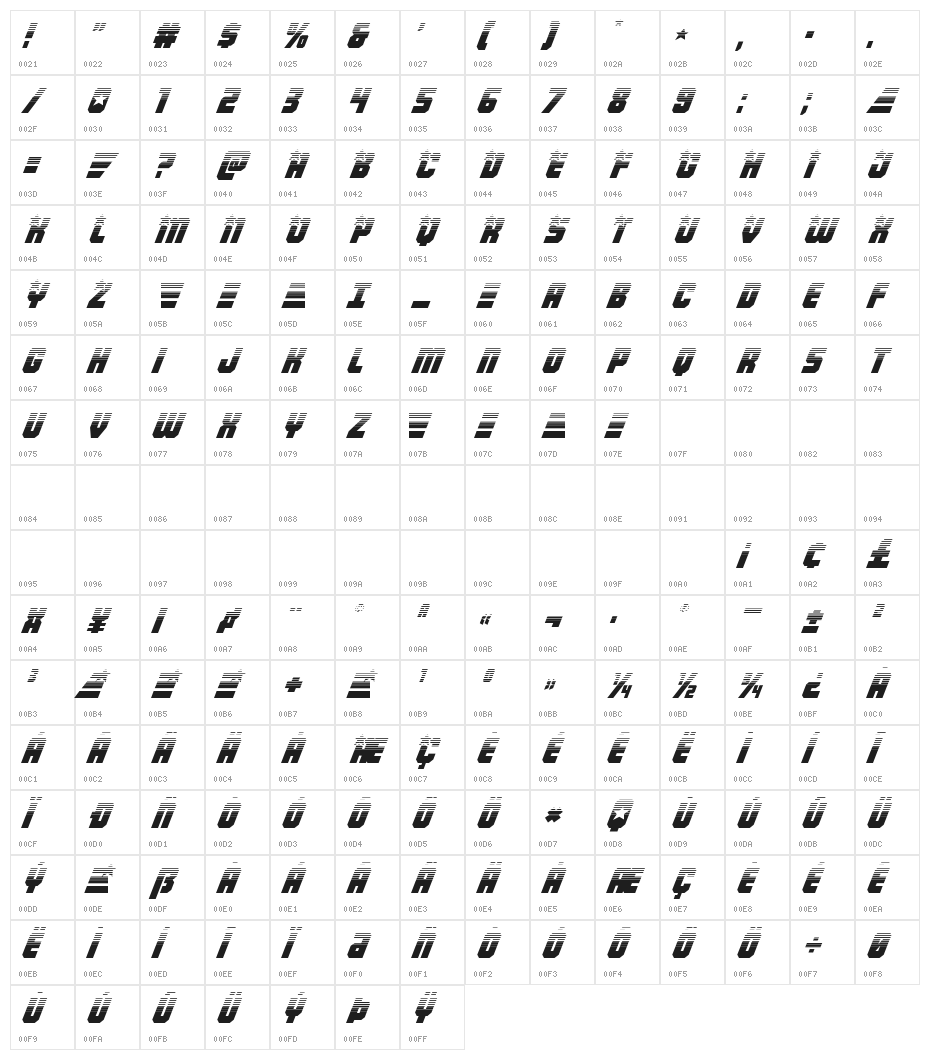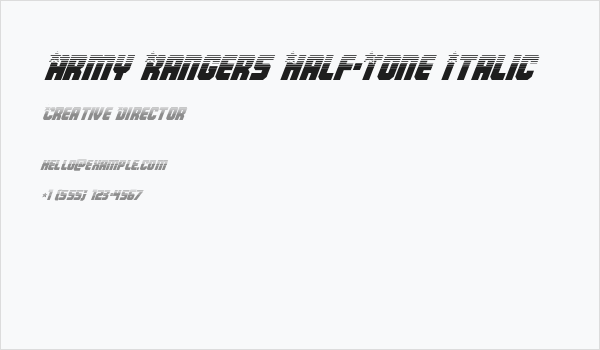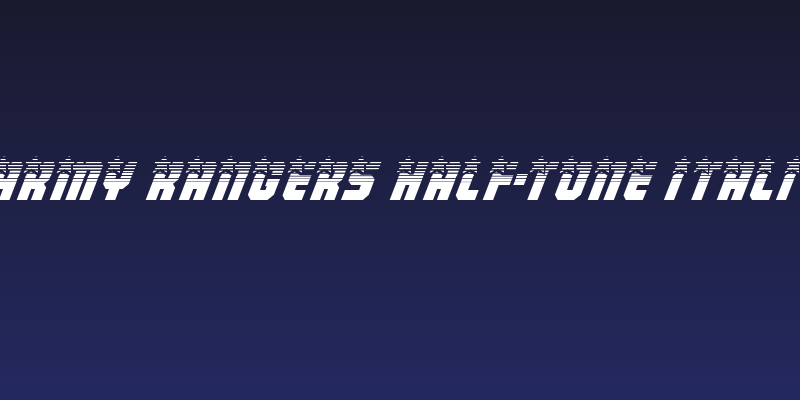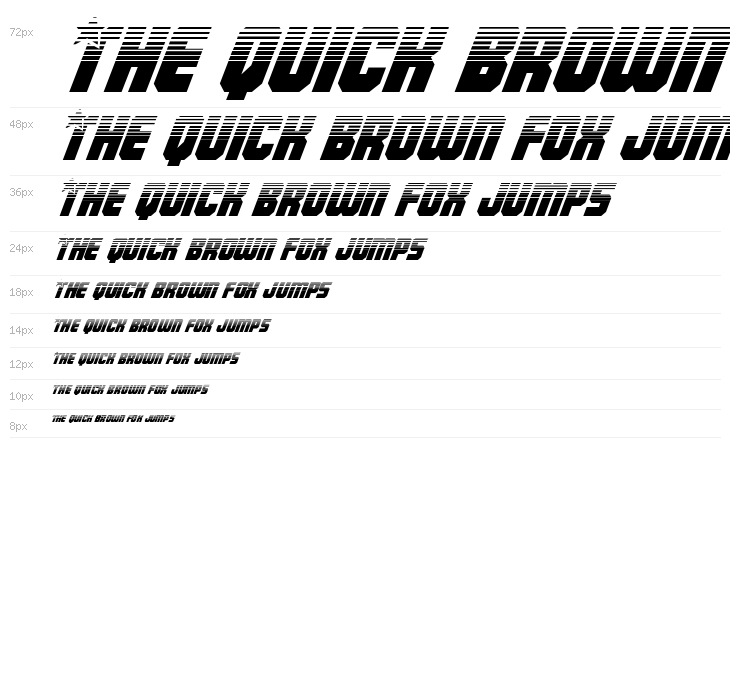
Army Rangers Half-Tone Italic Font
| Vorgeschlagene Projekte | Ideal for sports branding, action-themed posters, video game titles, and dynamic advertising campaigns. |